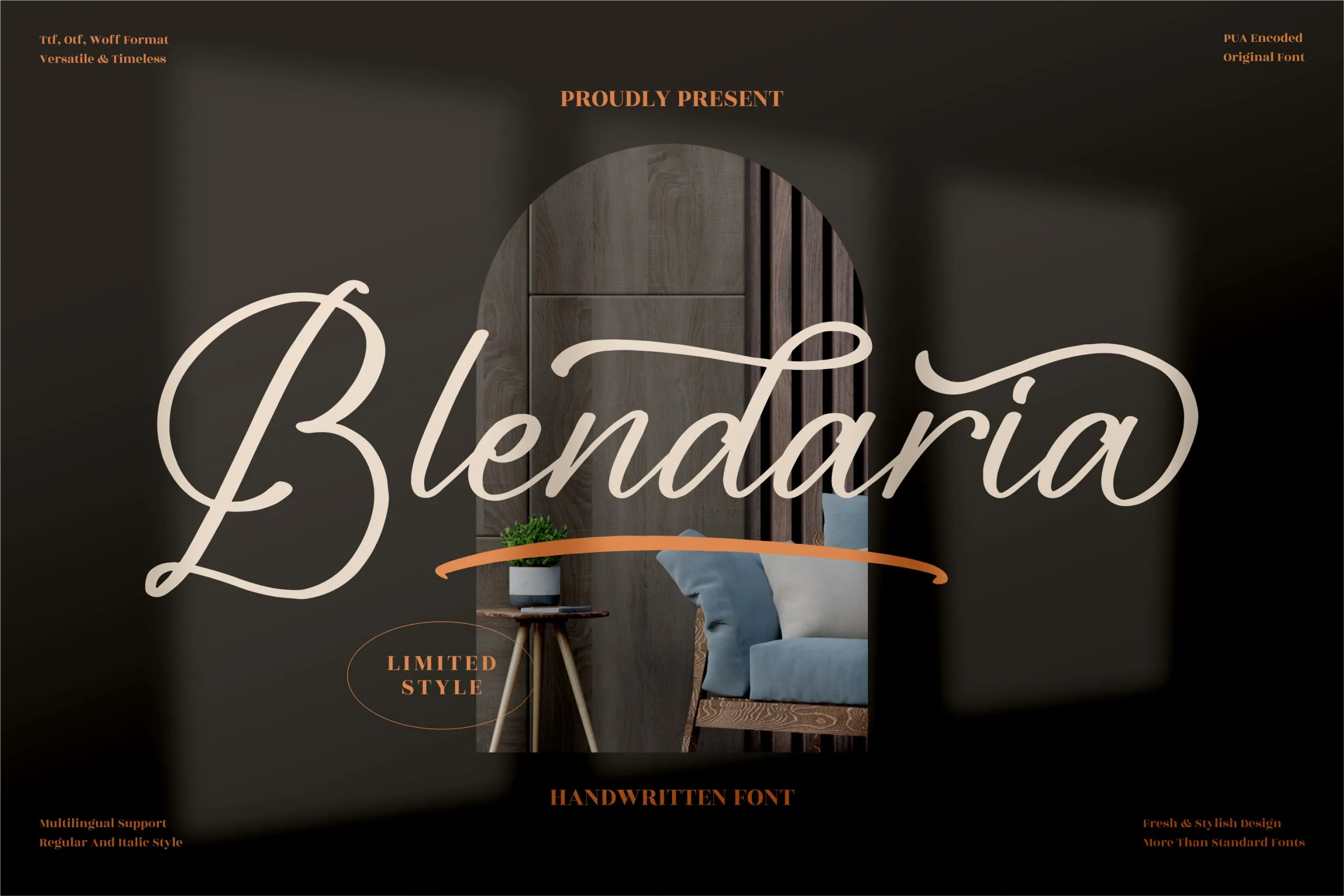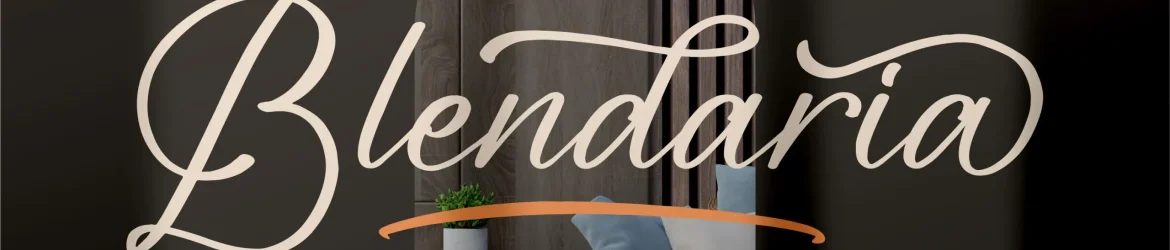
A Blendaria Font é uma fonte de estilo escrita que surgiu dos laços artísticos da tipografia com a arte do cálamo. Seja você designer, ilustrador ou criativo de qualquer campo, essa fonte perfeita para projetos pessoais e profissionais oferece um toque refinado e elegante à sua produção. Perfeita para os mais variados usos, como logomarcas, projetos de marca, design de móveis, embalagens de produtos, mugazinhos com mensagens inspiradoras, cartazes, sacolas de presente, camisetas personalizadas, capas de livros e até mesmo convites de casamento ou aniversário, Blendaria é a escolha perfeita para qualquer projeto que esteja em busca de um toque único e sofisticado. Seja você criando um design de luxo, uma publicação online, ou simplesmente personalizando seus próprios artigos, Blendaria oferece a consistência e o refinamento que seu projeto merece. Ela é ideal para qualquer projeto onde um toque de glamour e elegância seja desejado, tornando-a sua fonte preferida para produções de alta qualidade.